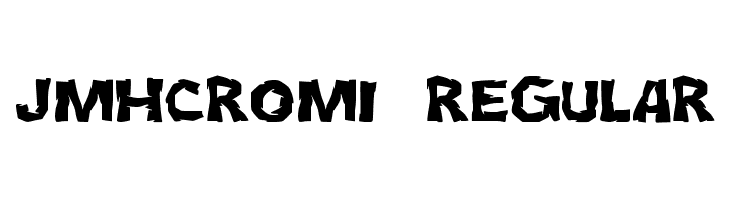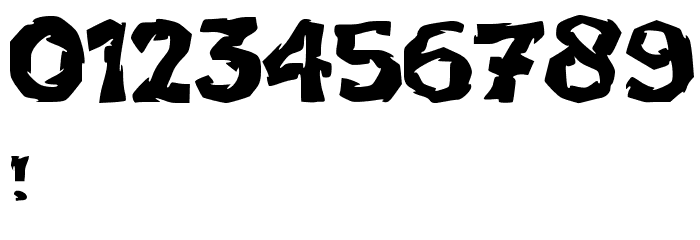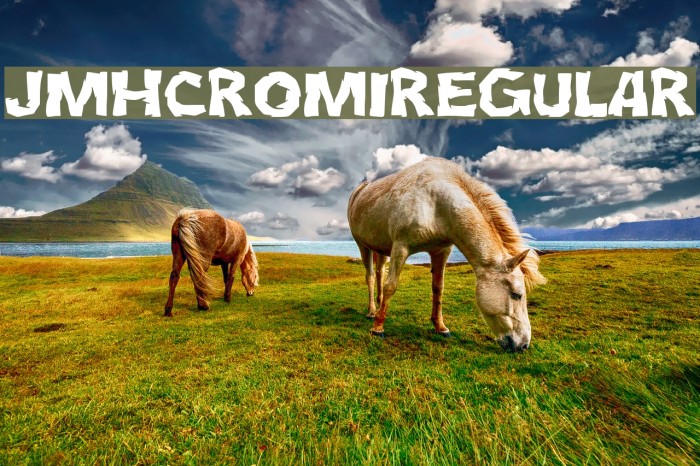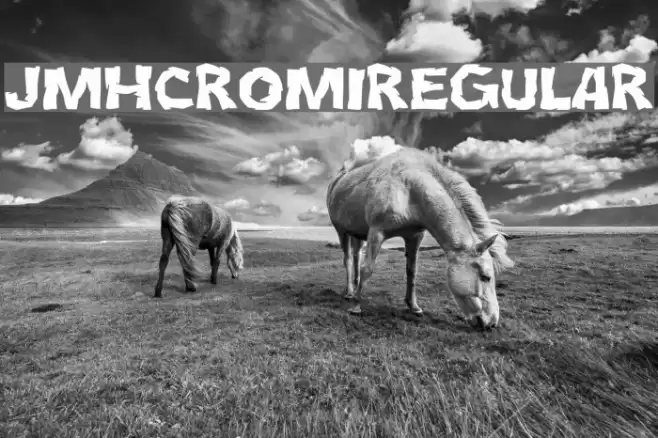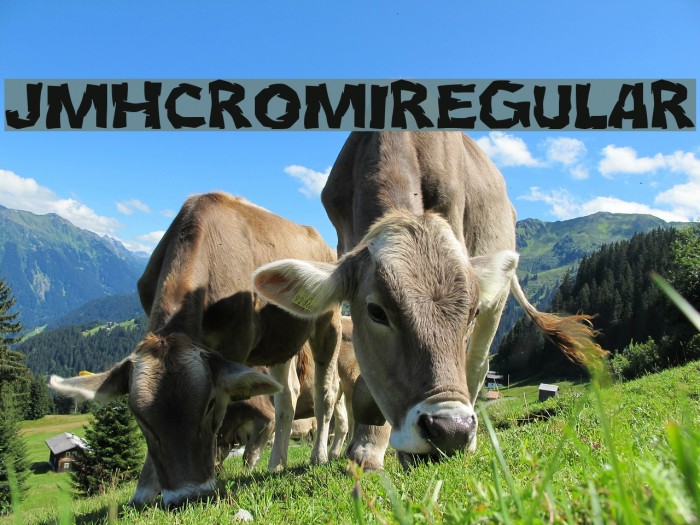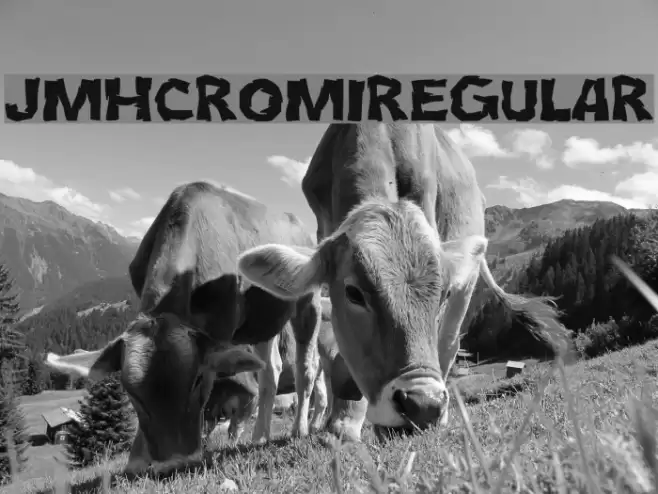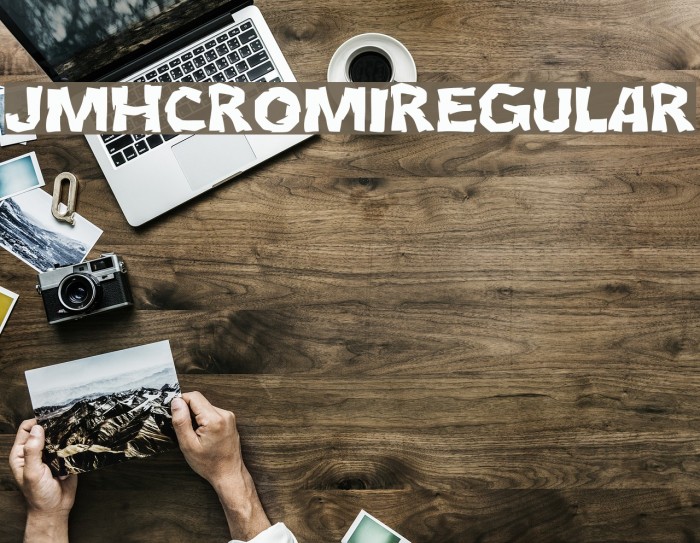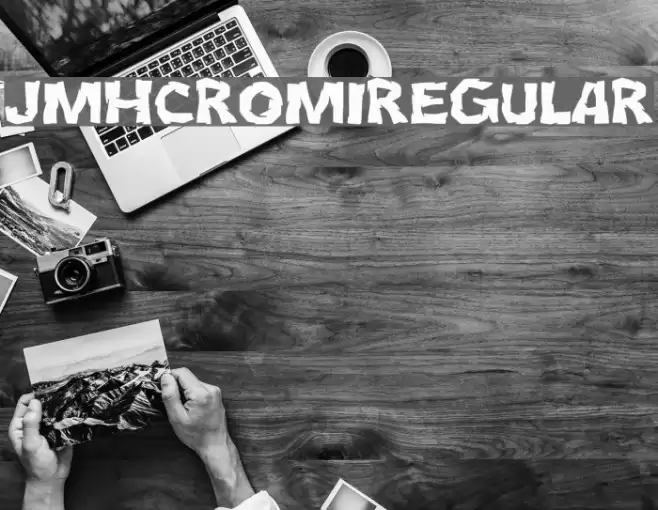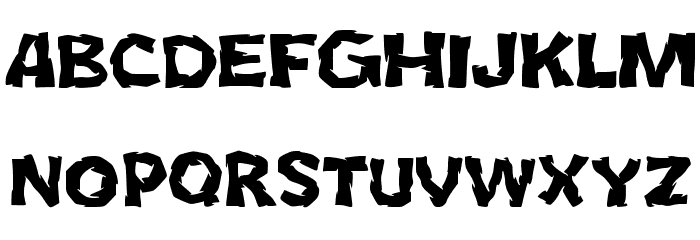
JMHCromI-Regular Font
| कंट्रास्ट | High |
| समग्र शैली | Decorative |
| उपयोग का मामला | Headlines, Logos |
| सुझाए गए प्रोजेक्ट | Perfect for posters, album covers, video game titles, and branding that requires a strong, edgy look. |